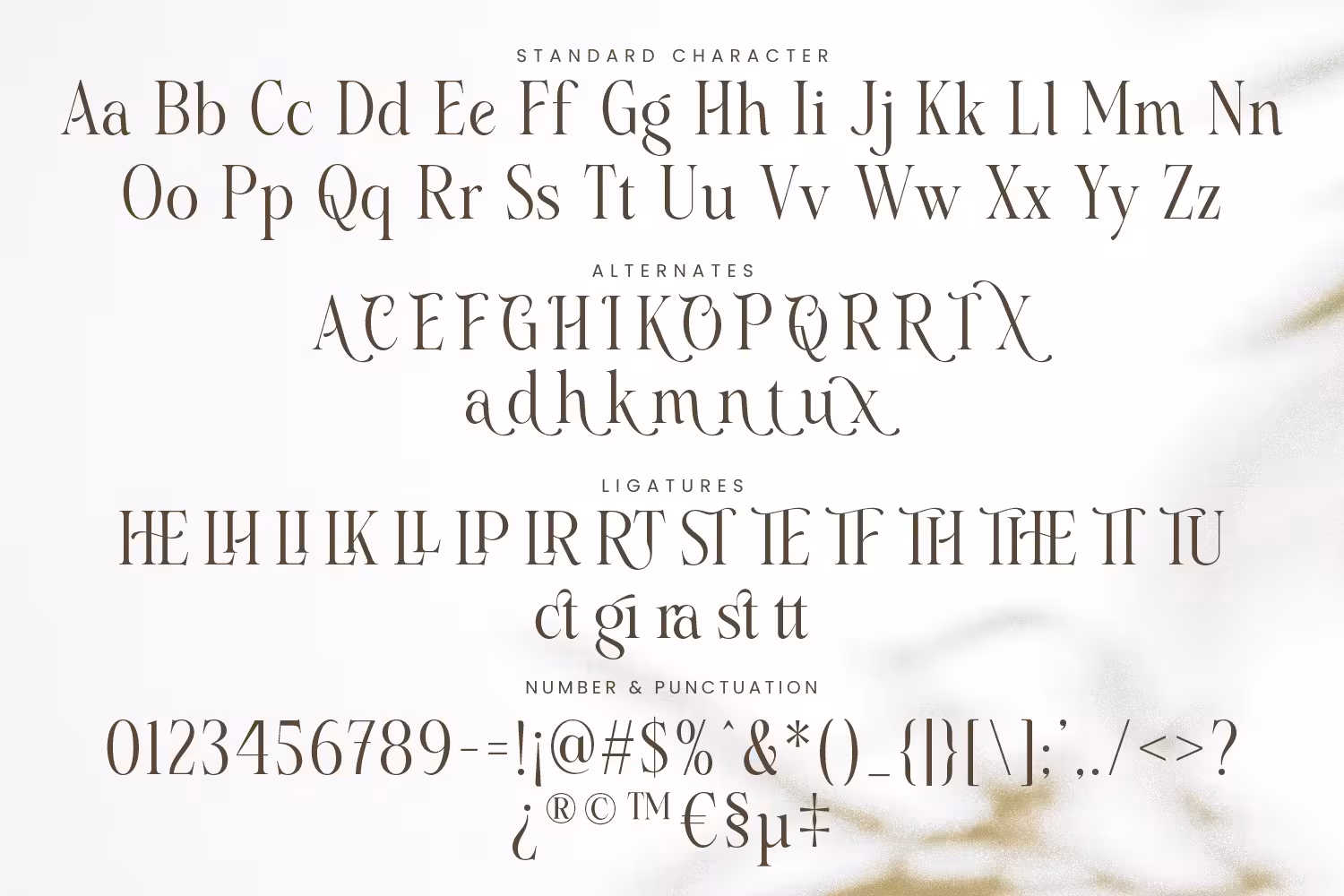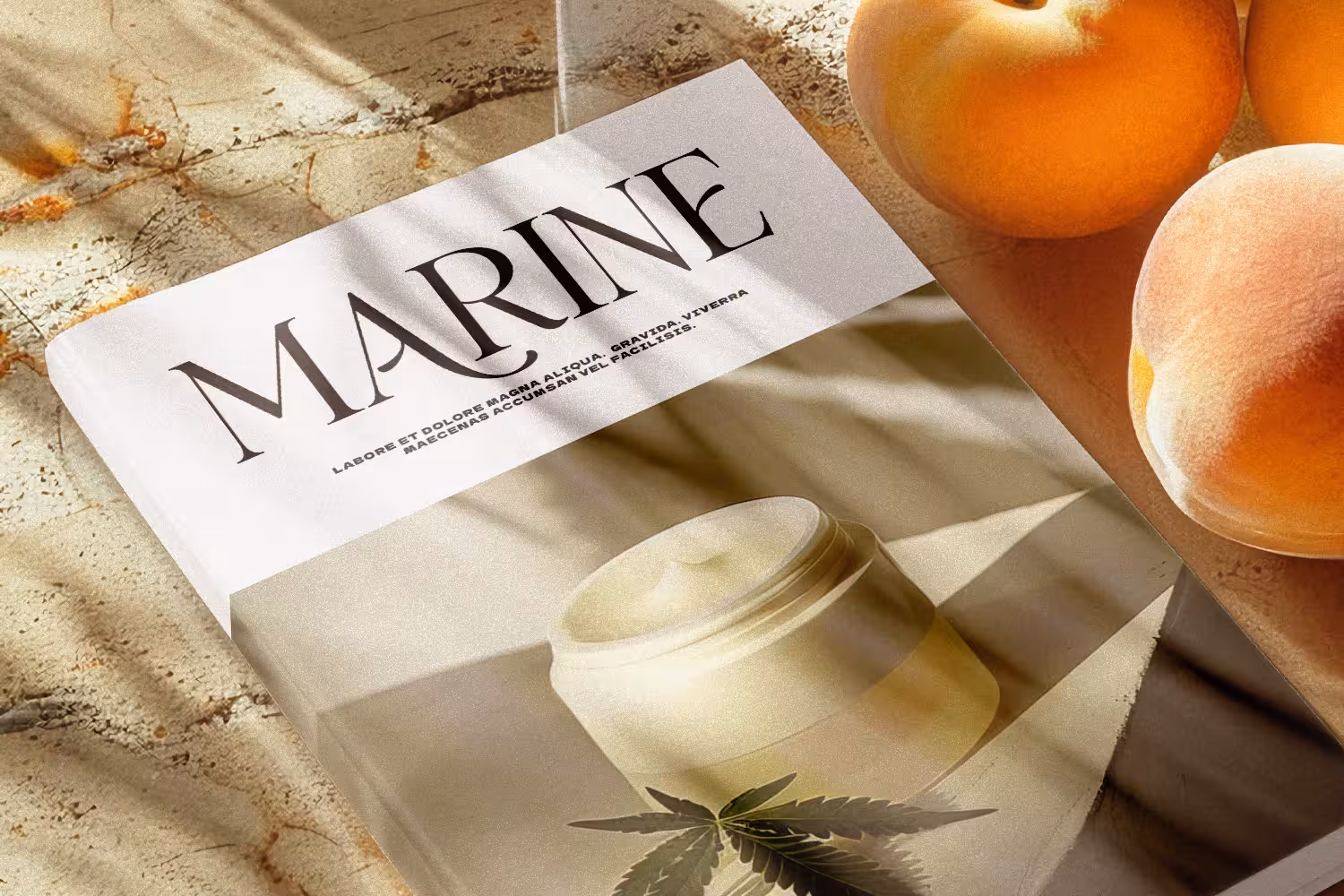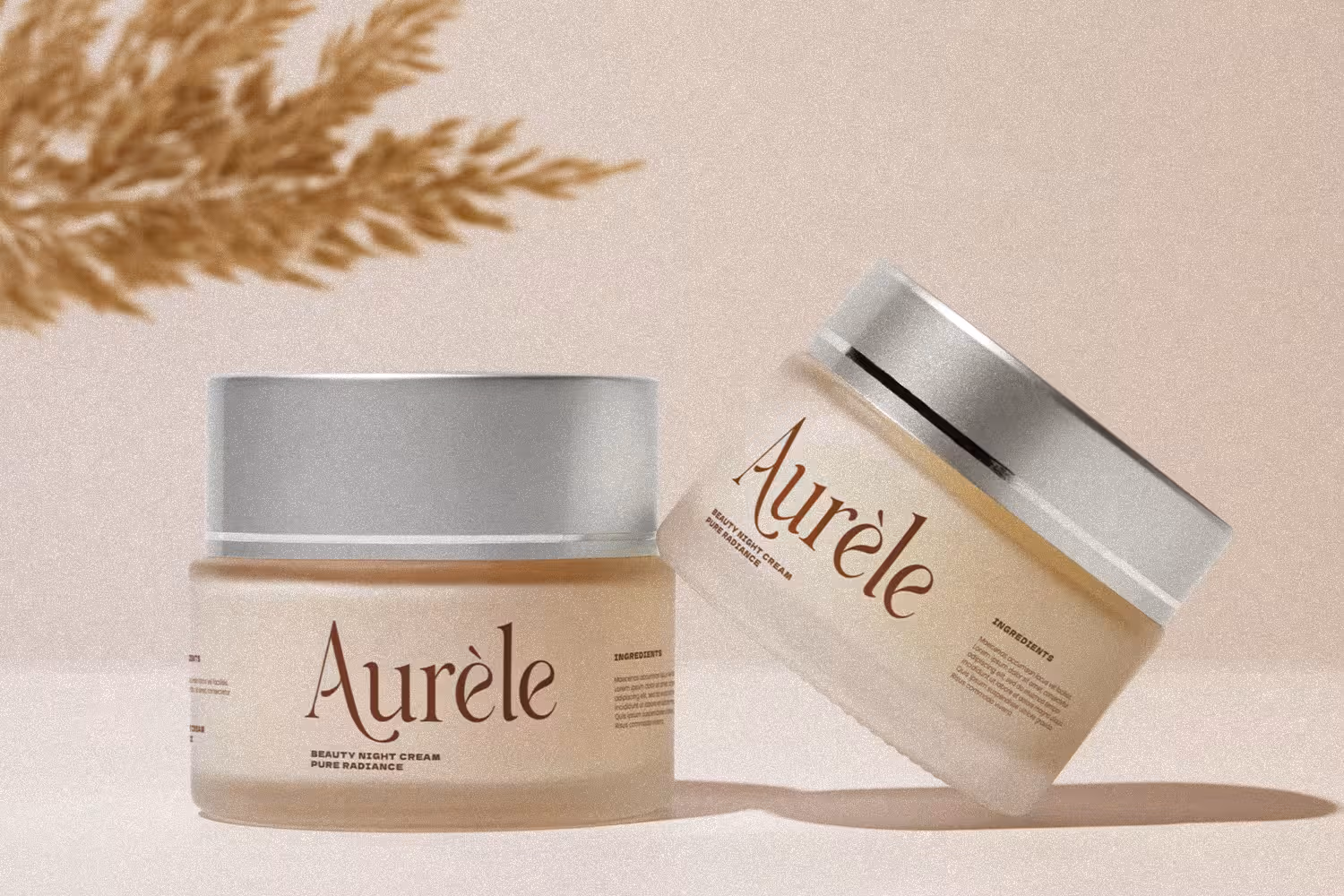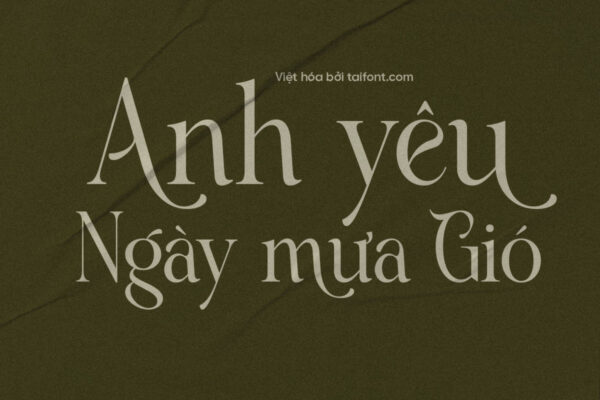
Giới thiệu về Font TF Cavalliera Việt hóa
TF Cavalliera Việt hóa là một font chữ mang vẻ đẹp thanh lịch, tinh tế và đầy cuốn hút, lý tưởng cho các thiết kế đòi hỏi sự sang trọng và đẳng cấp. Với những đường nét được trau chuốt cẩn thận, font này toát lên phong thái chuyên nghiệp và một chút mềm mại, tạo ấn tượng mạnh mẽ nhưng vẫn rất dễ chịu.
Cavalliera là lựa chọn hoàn hảo để nâng tầm giá trị thẩm mỹ trong các lĩnh vực:
- Thiết kế thời trang: Hoàn hảo cho các thương hiệu thời trang cao cấp, nhãn mác sản phẩm, lookbook, hoặc các ấn phẩm quảng bá bộ sưu tập. Font này giúp truyền tải sự tinh tế, phong cách và sự độc đáo của từng thiết kế.
- Mỹ phẩm: Lý tưởng để sử dụng trên bao bì sản phẩm, catalogue, hoặc các chiến dịch marketing, giúp khẳng định chất lượng và sự cao cấp của thương hiệu mỹ phẩm. Font Cavalliera sẽ làm nổi bật vẻ đẹp của sản phẩm, thu hút ánh nhìn của khách hàng.
Với TF Cavalliera Việt hóa, bạn có thể dễ dàng tạo ra những thiết kế không chỉ đẹp mắt mà còn truyền tải được thông điệp về sự tinh tế, sang trọng và đẳng cấp, góp phần nâng tầm giá trị cho thương hiệu của bạn.
Font Việt hóa TF Cavalliera – Nhiều glyphs đẹp